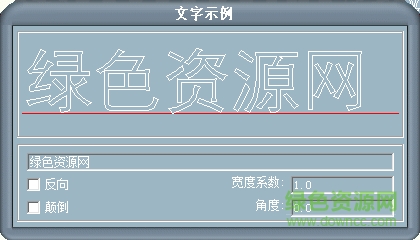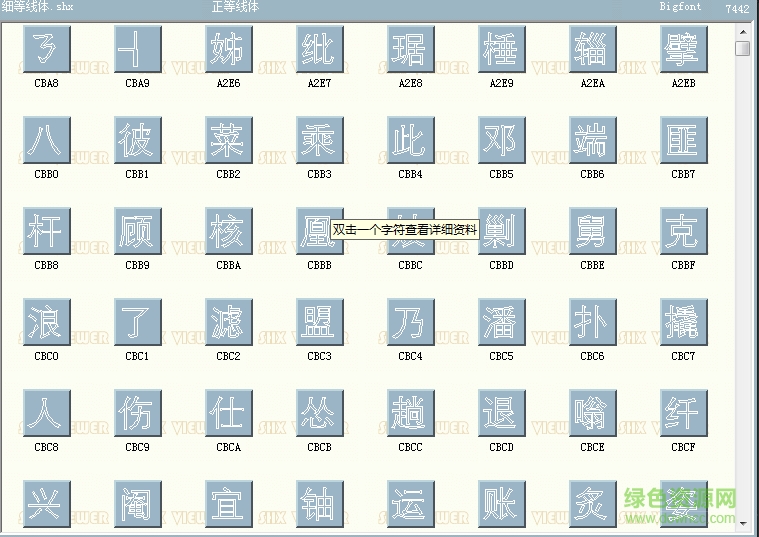
cad細(xì)等線體.shx是一款實(shí)用的的cad字體,比起windows的truetype字庫,shx字體顯示速度更快.字體大小設(shè)置更加精確,適合繪圖設(shè)計(jì),有需要者快來綠色資源網(wǎng)下載吧!
與truetype字體相比,shx字體美觀效果不夠理想,但在工程中尚可滿足需要。shx字體相當(dāng)于硬筆書法,在模擬毛筆書法上存有差距。由于shx字體與windows的truetype字體互有所長,在工程中可取長補(bǔ)短,酌情使用!